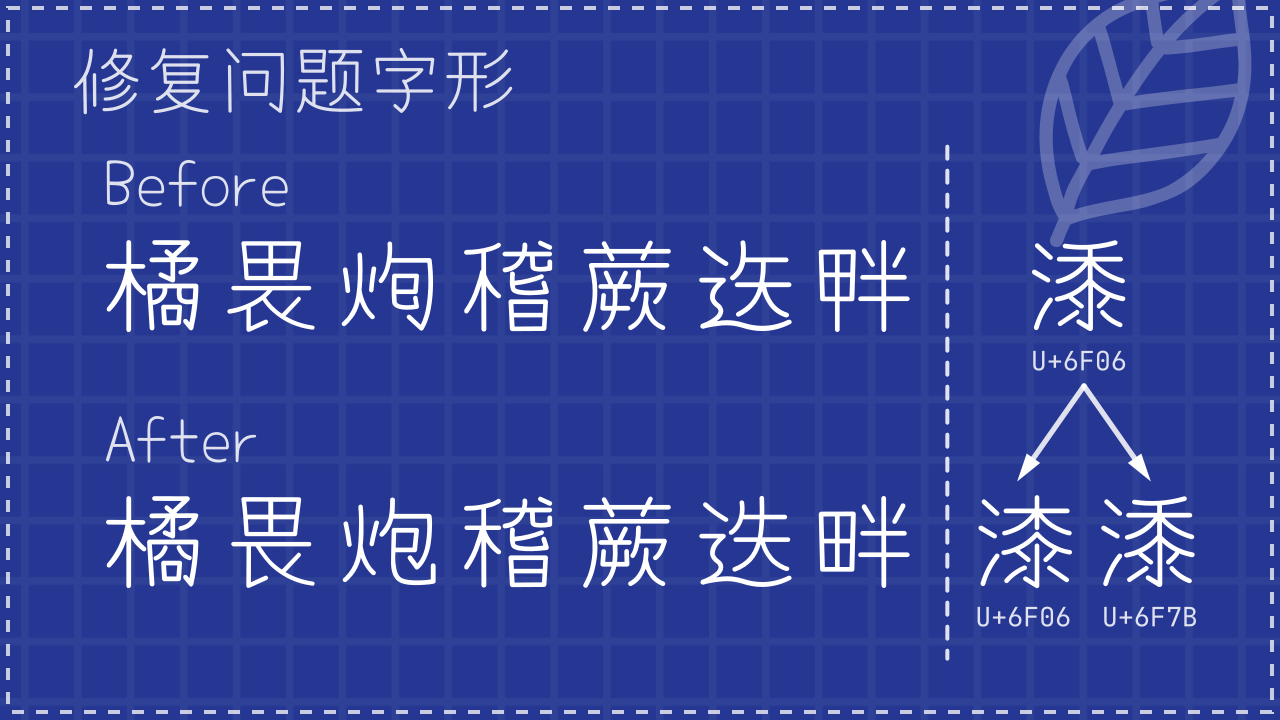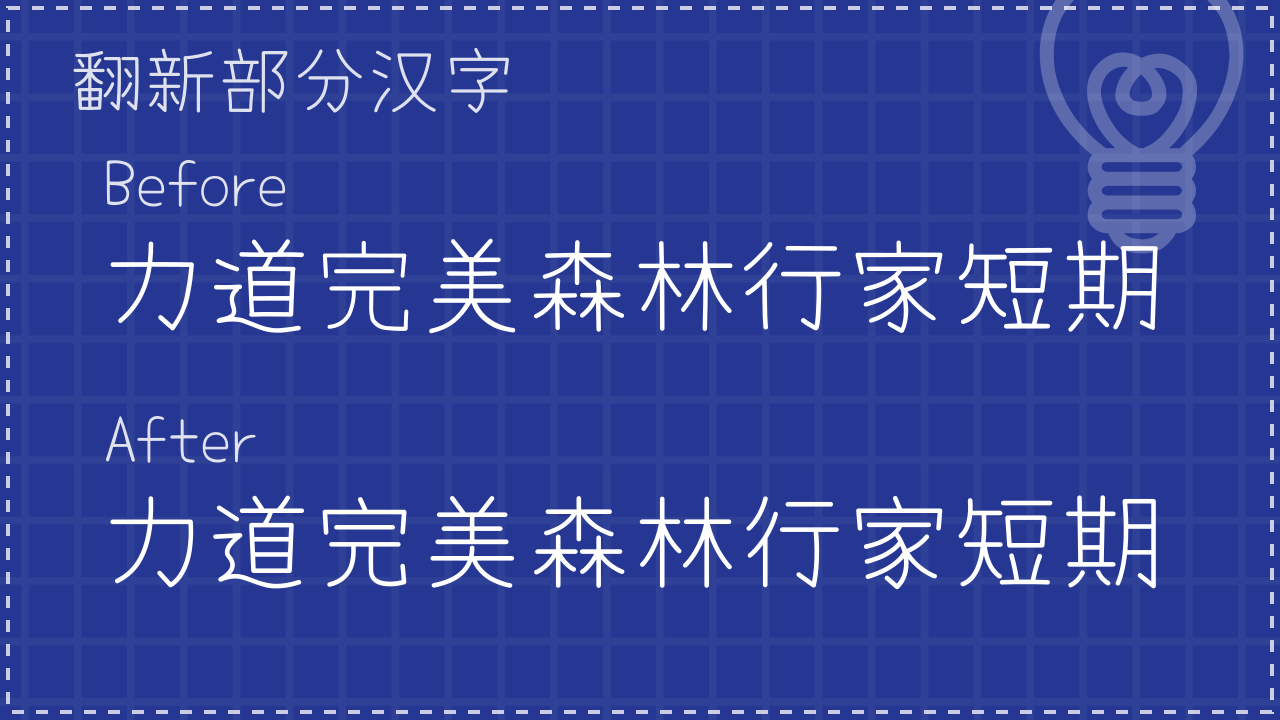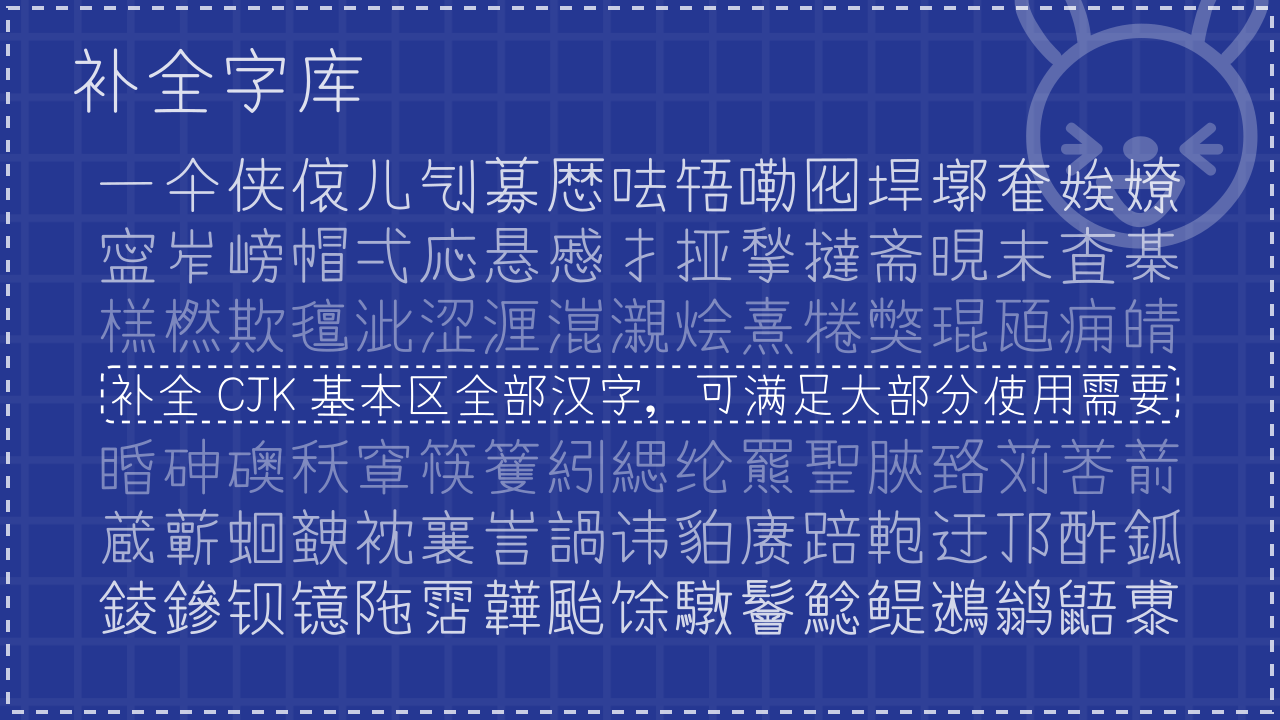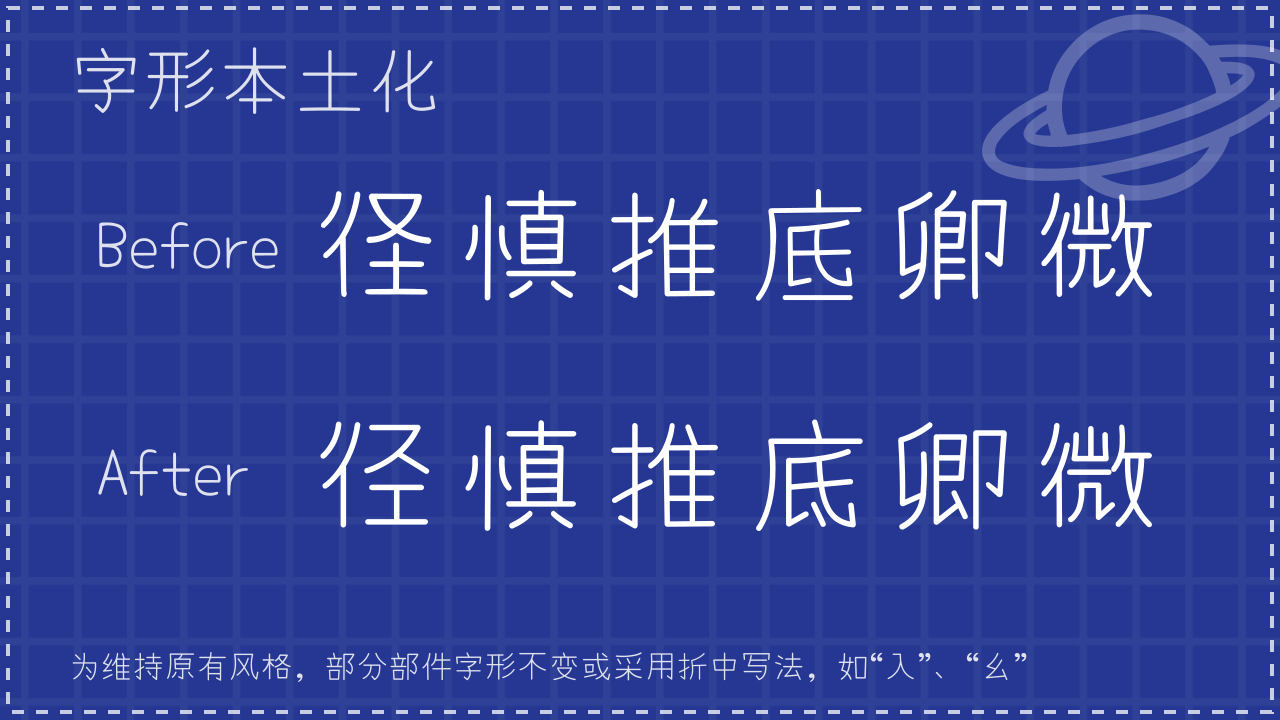
有梦体 / 有夢體 / Yomeng Script
本字体由 Yomogi 字体二次开发而成。
介绍
1. 补全字库
补全 CJK 基本区内全部汉字,可满足大部分使用需要。
补全字库,补全CJK基本区全部汉字,可满足大部分使用需要-刊刻Kntuk
2. 字形本土化
将大部分汉字调整为更符合陆标的字形,少部分汉字或部件为维持原有风格,保留原有字形或采用折中写法。
字形本土化Before与After对比,展示“徑慎推底卿微”到“径慎推底卿微”,底部说明为维持原有风格部分部件采用折中写法-刊刻Kntuk
3. 翻新部分汉字
翻新原字体当中部分风格差异较大的汉字,加强风格一致性。
翻新部分汉字,Before力道完美森林行家短期,After力道完美森林行家短期-刊刻Kntuk
4. 修复问题字形
修复原字体中一些笔画或码位存在问题的汉字。
这张图展示了修复问题字形的Before和After对比,比如“炮”字的修正,还有“漆”字从U+6F06修正为U+6F06和U+6F7B。-刊刻Kntuk
• 本人并非专业的字体设计师,且字数庞大,制作时间跨度较长,制作方法又经过多次调整,因此难免会出现部分汉字的质量或风格参差不齐的状况。